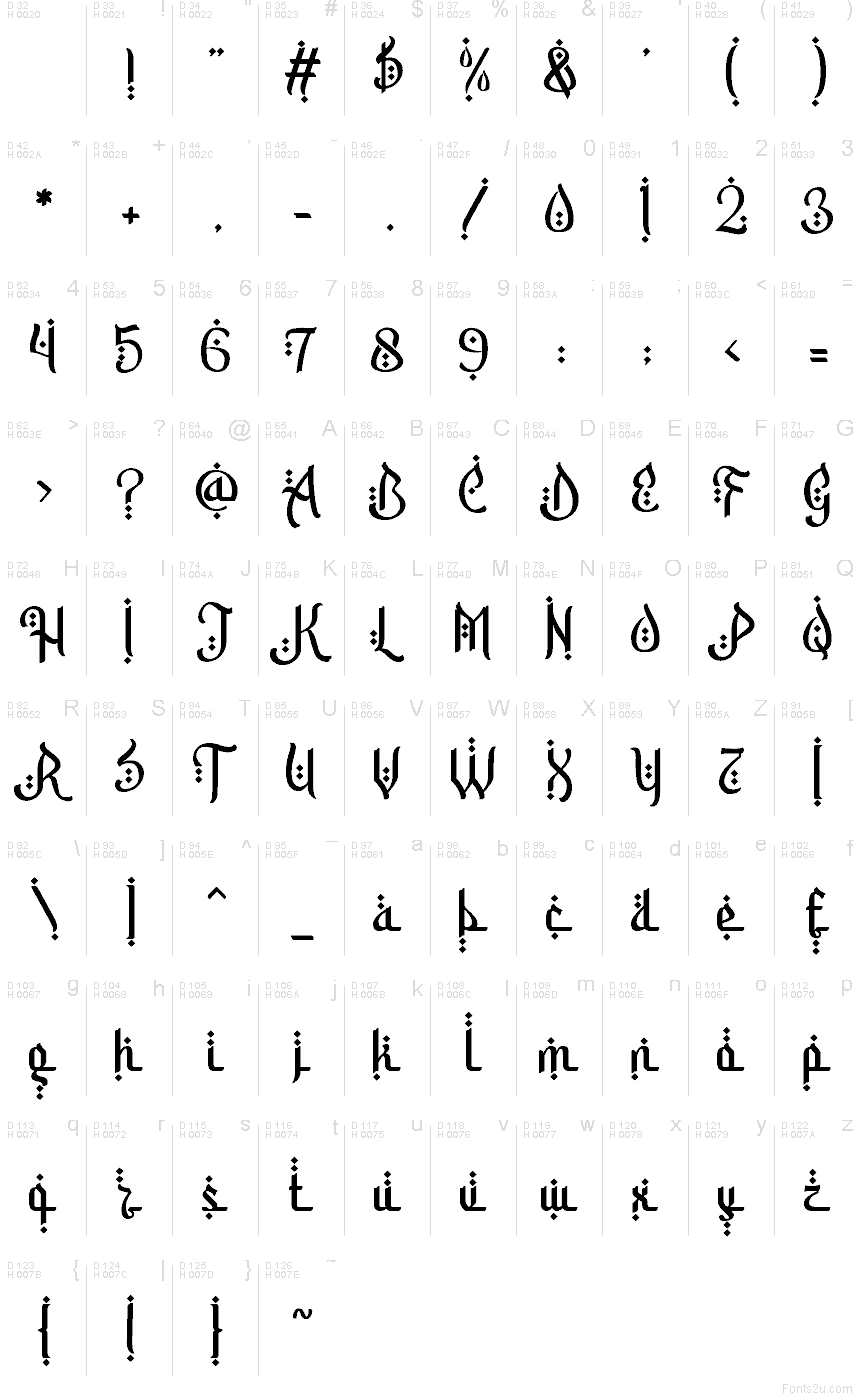
Majidi Mirage Two
Majidi Mirage Two od Putracetol Studio je bezplatné písmo v arabskom štýle, definované vysokými vertikálnymi ťahmi, zúženými krivkami a opakujúcimi sa diamantovými bodkami, ktoré okamžite evokujú arabskú kaligrafiu. Tento motív dodáva znakom obradný rytmus, pričom úzke zvislice a ladné krivky vytvárajú ostrú a výraznú siluetu, ktorá vyniká nad ostatnými.
Pri brandingu orientálnych reštaurácií, kultúrnych plagátoch, ramadánových akciách, obaloch produktov či titulkoch má Majidi Mirage Two dostatočnú prítomnosť na to, aby orámovalo krátky text s jasným regionálnym odkazom. Vrstvené diamantové akcenty a predĺžené ťahy z neho robia prirodzenú voľbu pre vývesné štíty, grafiku na sociálne siete a dekoratívne nadpisy, kde na atmosfére záleží rovnako ako na samotnom texte.